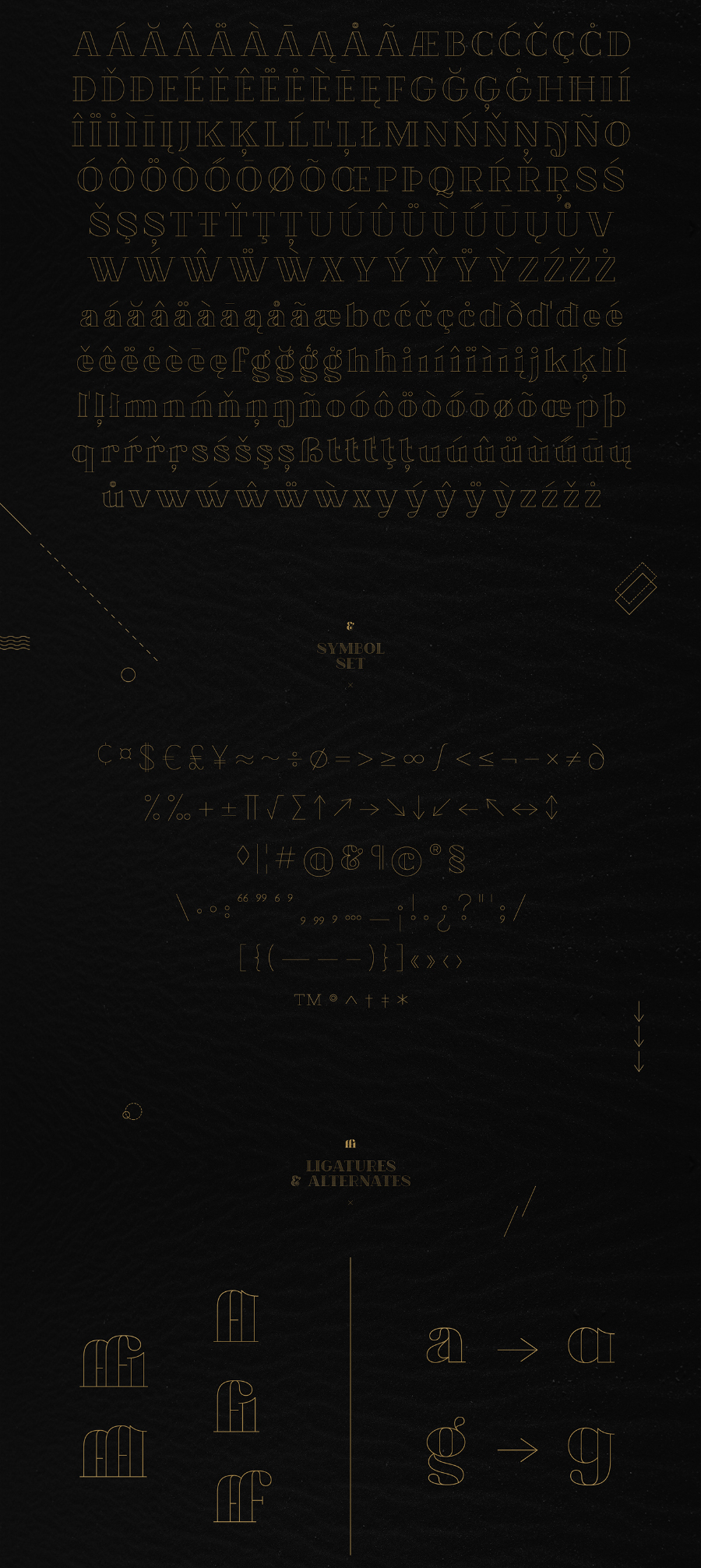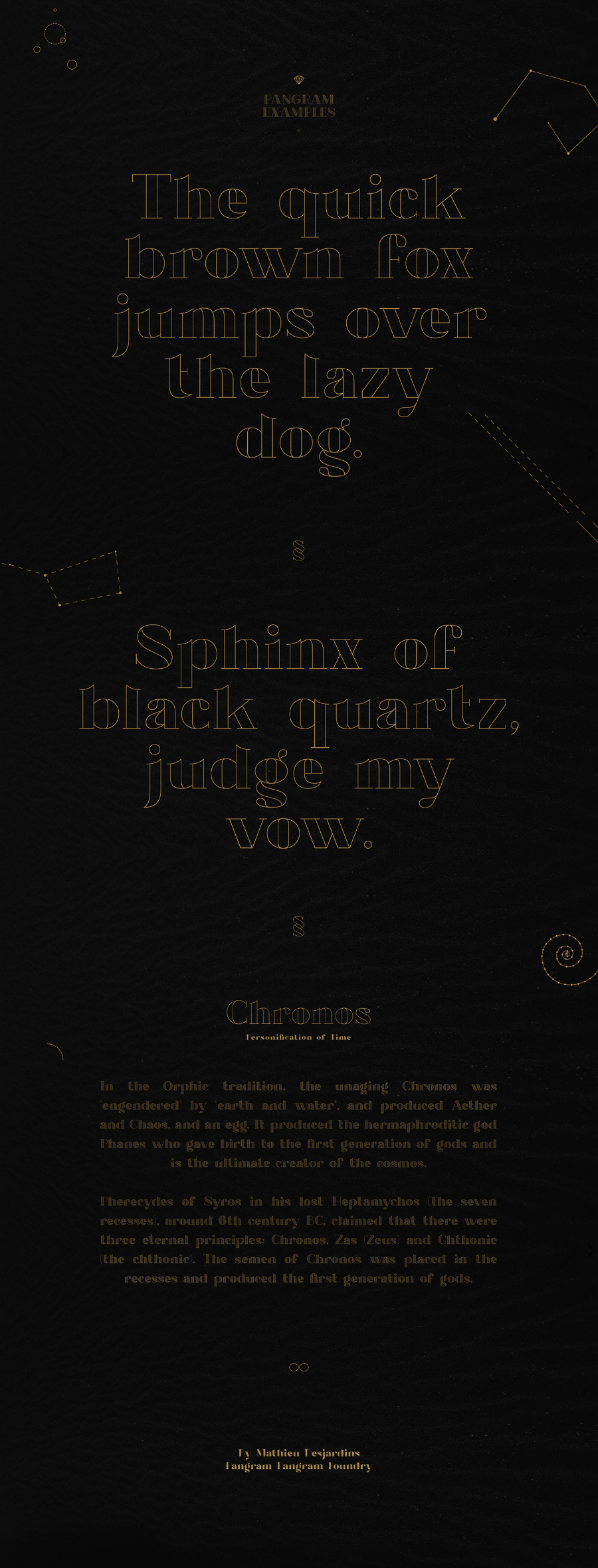
Chronos Serif免费字体
Chronos Serif Free Typeface
Chronos Serif免费字体是一个优雅的显示衬线有3个变种。充满细节和精致的曲线,肯定会提升您的高端项目。这个字体不只是一个经典的衬线字体。它具有令人着迷的特征,对于品牌和标识来说是完美的。这也是杂志和时尚产品的时尚和伟大。